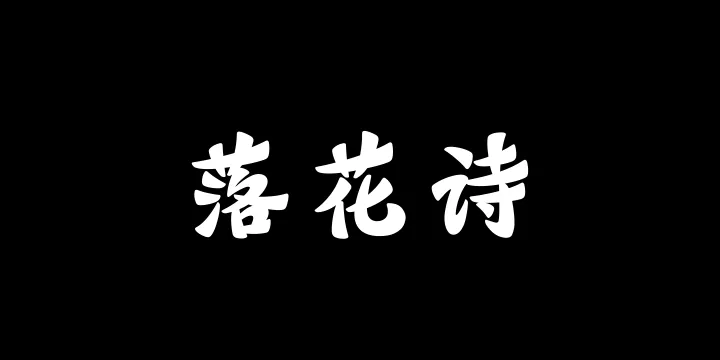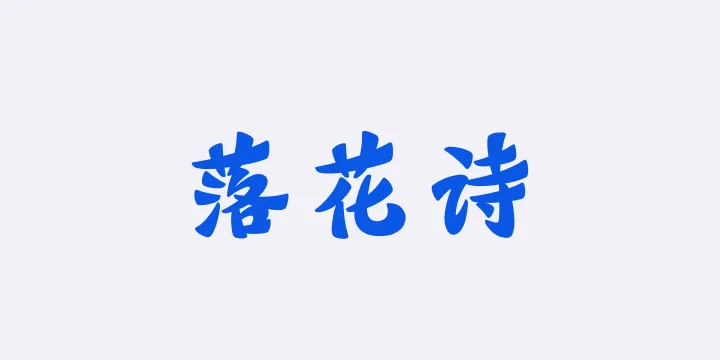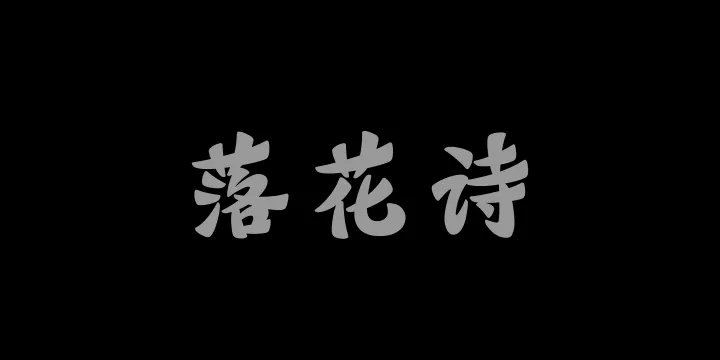
山海落花诗 95W By 山海字库 商用字体
字体简介: 山海落花诗95W,是一款全新的楷体字体,是山海落花诗字体家族系列中的特粗款,编号95W,包含汉字9169个,符号200+个。该字体字形优美文雅,诗意内敛,取楷体细腻的书写笔画,书法的运笔走势蕴含其中,流畅自然,蕴含东方审美韵味,尽显优雅从容,秀雅清新。